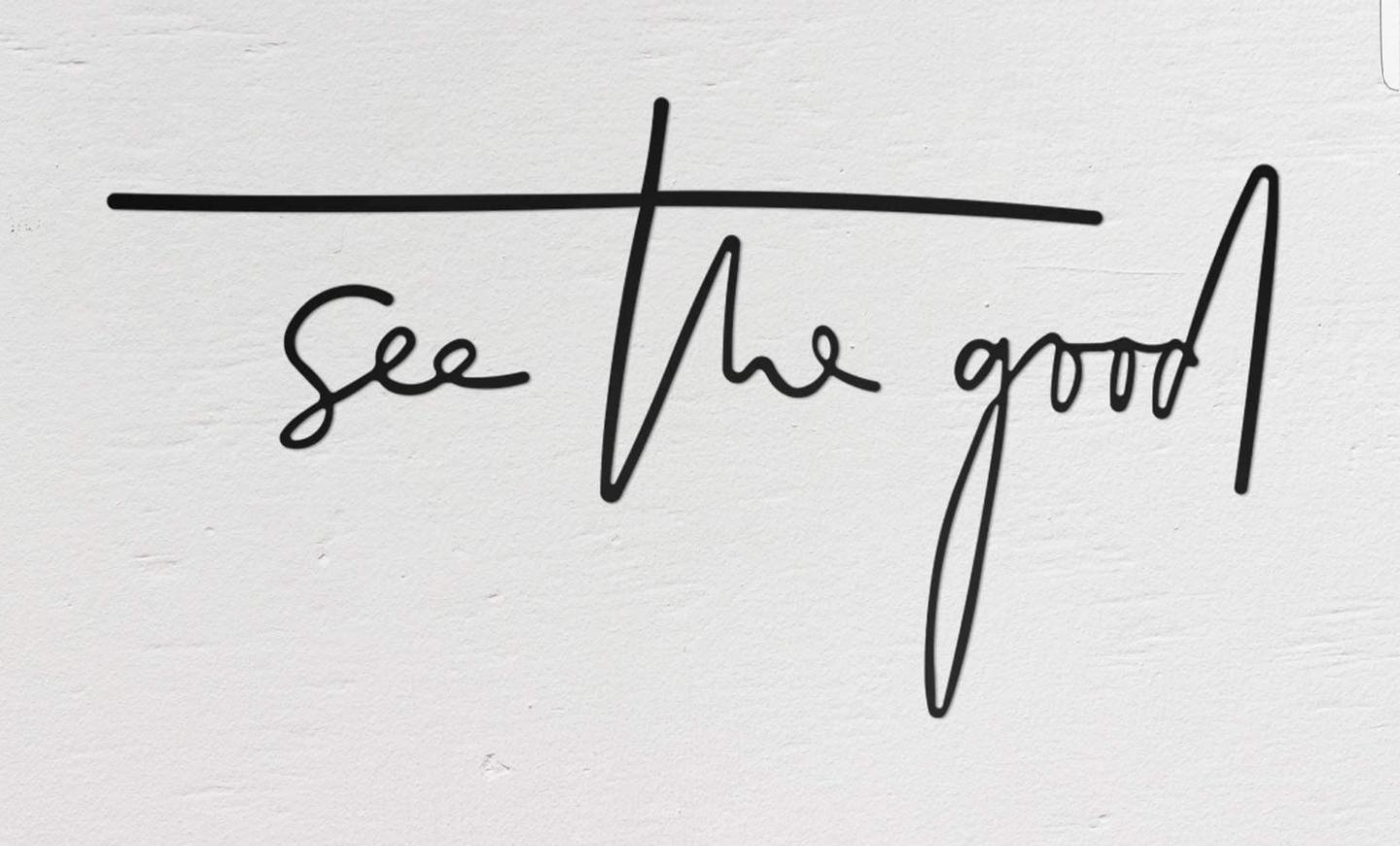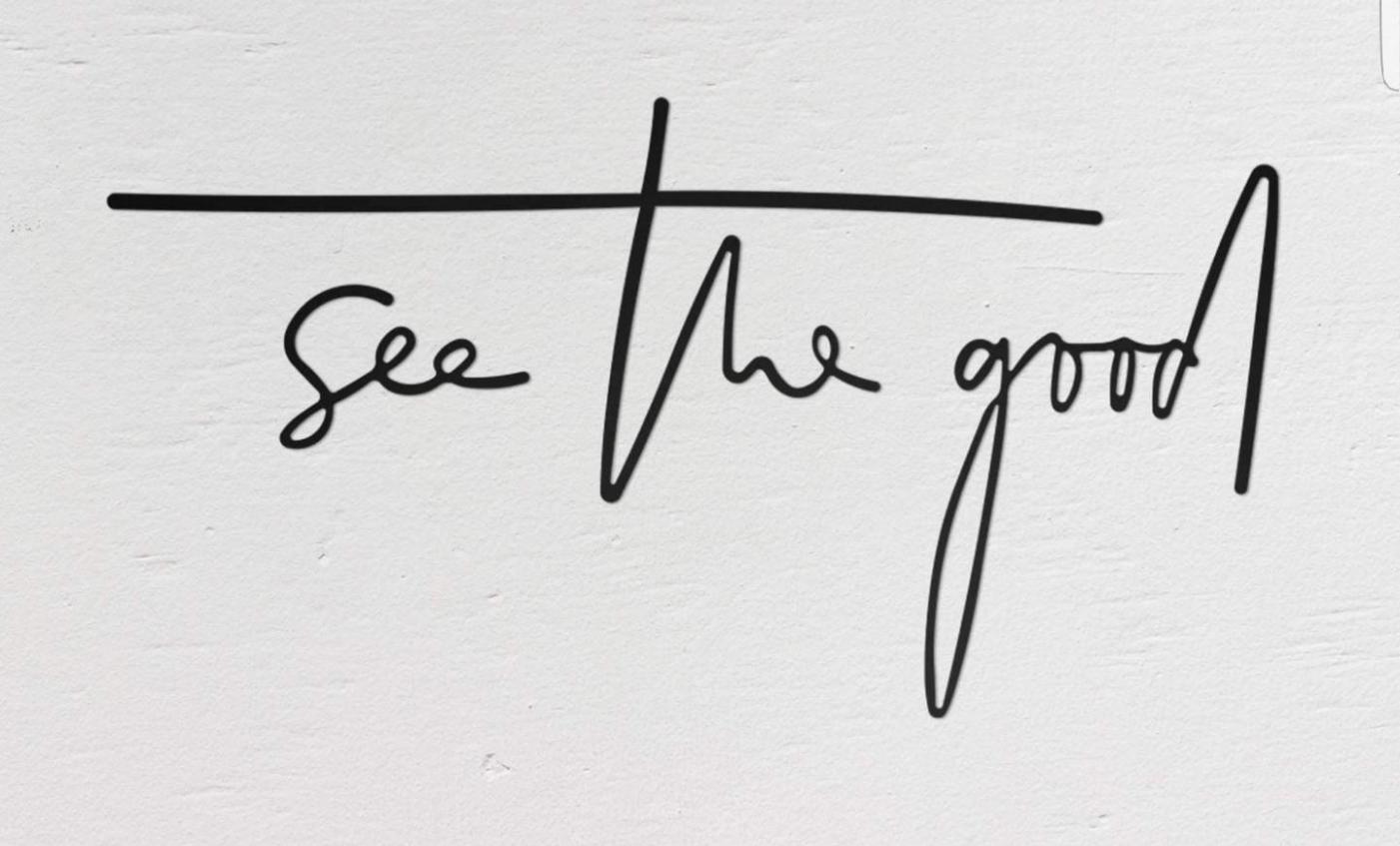
Suche Schriftart für Wandschrift
Kann mir jemand weiterhelfen,  welche Schriftart das ist? Oder eine ähnliche Schriftart nennen?
alles deutet auf Lettering ohne Font hin.
Absolut nachvollziehbar – allerdings sind vergleichbare Produkte des Anbieters Northshire durchaus mit "fertigen" Fonts aus dem Hause Creative Markt erstellt worden. Wenn ich wetten müsste, würde ich in diesem Fall auf eine lizenzierbare Schrift mit vielen Alternates setzen und nicht vermuten, dass dafür ein/e Lettering-Künstler/in beauftragt wurde.
Auch ähnlich: https://creativemarket.com/Nickylaatz/2226871-Signature-Collection-Script-Font
… und nicht vermuten, dass dafür ein/e Lettering-Künstler/in beauftragt wurde.
Von einem externen Auftrag hat ja auch keiner gesprochen. Es gibt mehr Möglichkeiten als Font oder beauftragter Lettering-Künstler.
Und ich bezog meine Einschätzung auch nicht allein auf die wiederholenden Buchstaben. Der vermeintliche Font müsste quasi alle drei Wörter als Catchwords enthalten, damit das als Font funktioniert.